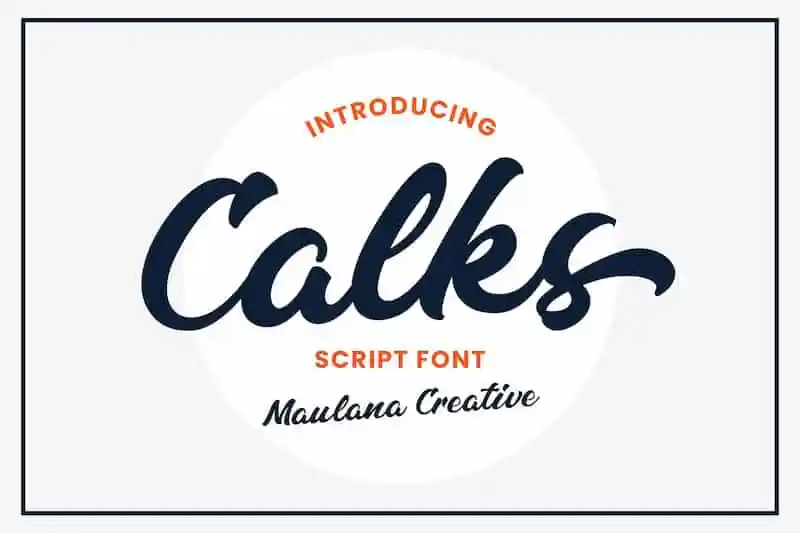
Calks Script Font – Download Grátis
Calks Script Font é uma fonte script bold criada pela Maulana Creative com um fluxo natural e elegante. Esta coleção perfeita para personal branding apresenta uma variedade de opções que se destacam por sua versatilidade. Esta fonte é ideal tanto para aplicativos pessoais, como marca pessoal e convites de casamento, quanto para campanhas publicitárias. Suas linhas finas e acentos distintos criam um aspecto sofisticado, adequado tanto para o mundo digital quanto do papel. A Calks Script Font oferece uma versão que pode ser usada em qualquer aplicação visual, tornando-a uma escolha segura para designers de todo tipo procurarem uma fonte script elegante e moderna.